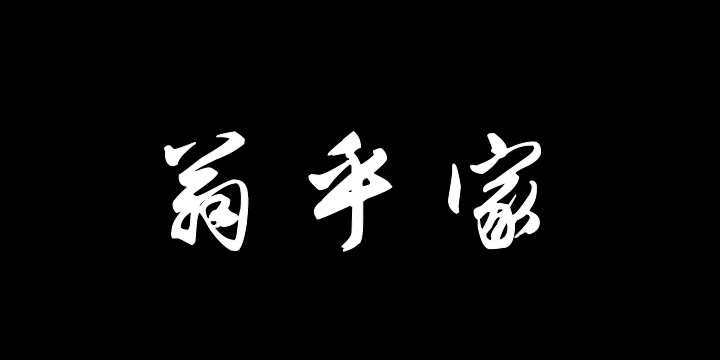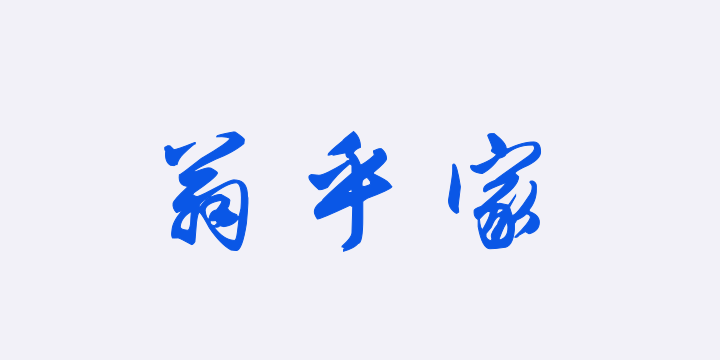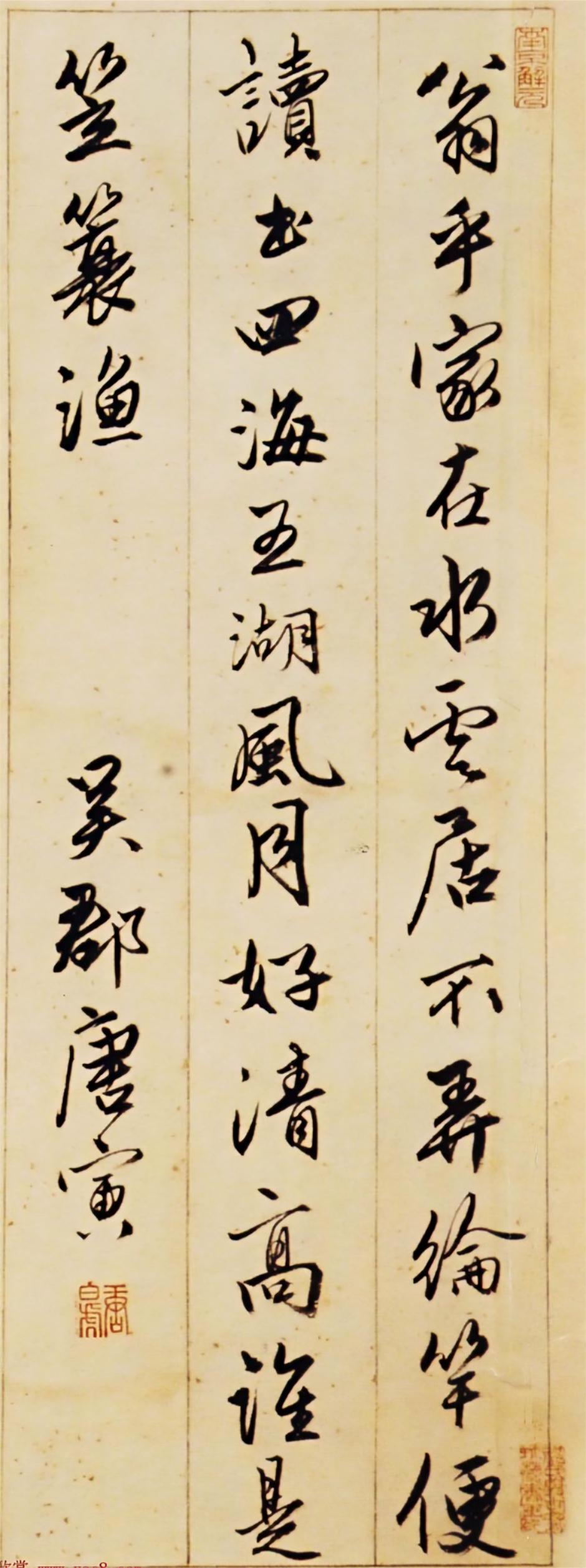
汉标唐伯虎七言绝句四条屏
字体全名: 汉标唐伯虎七言绝句四条屏
铸字厂: 真迹小字库
字体简介: 下载须知:本字库非标准GB2312字库。本字库只包含了唐伯虎《七言绝句四条屏》真迹上的“144个字”。明代唐伯虎行书作品欣赏《七言绝句四条屏》纸本,57.2×22cm×4,广东省博物馆藏。
所属分类: 行书毛笔字手写体书法